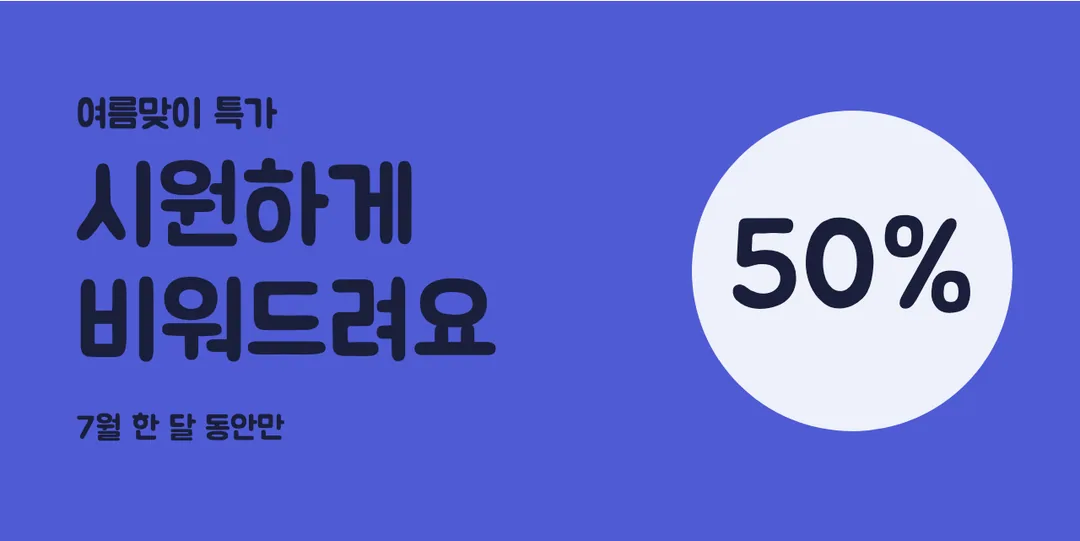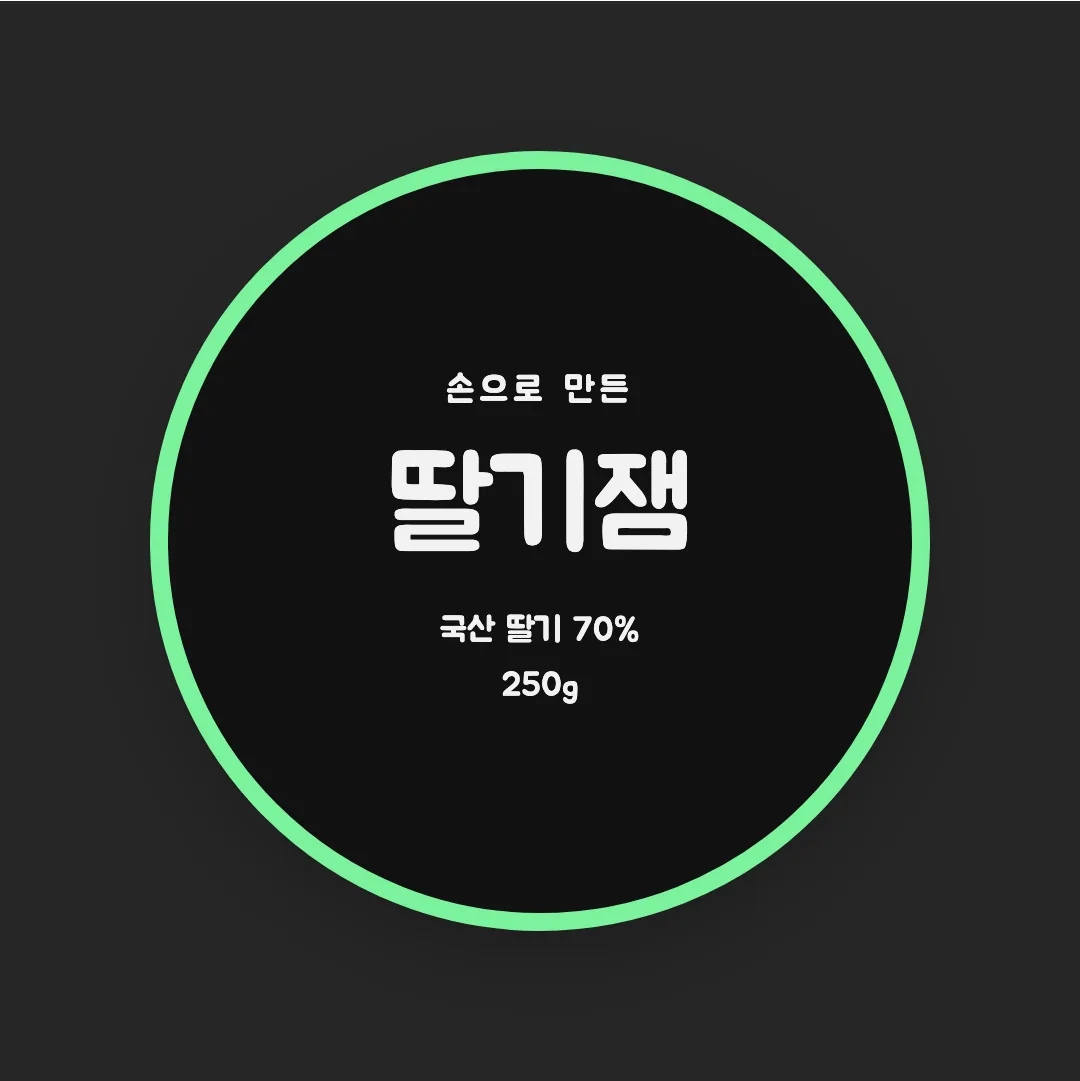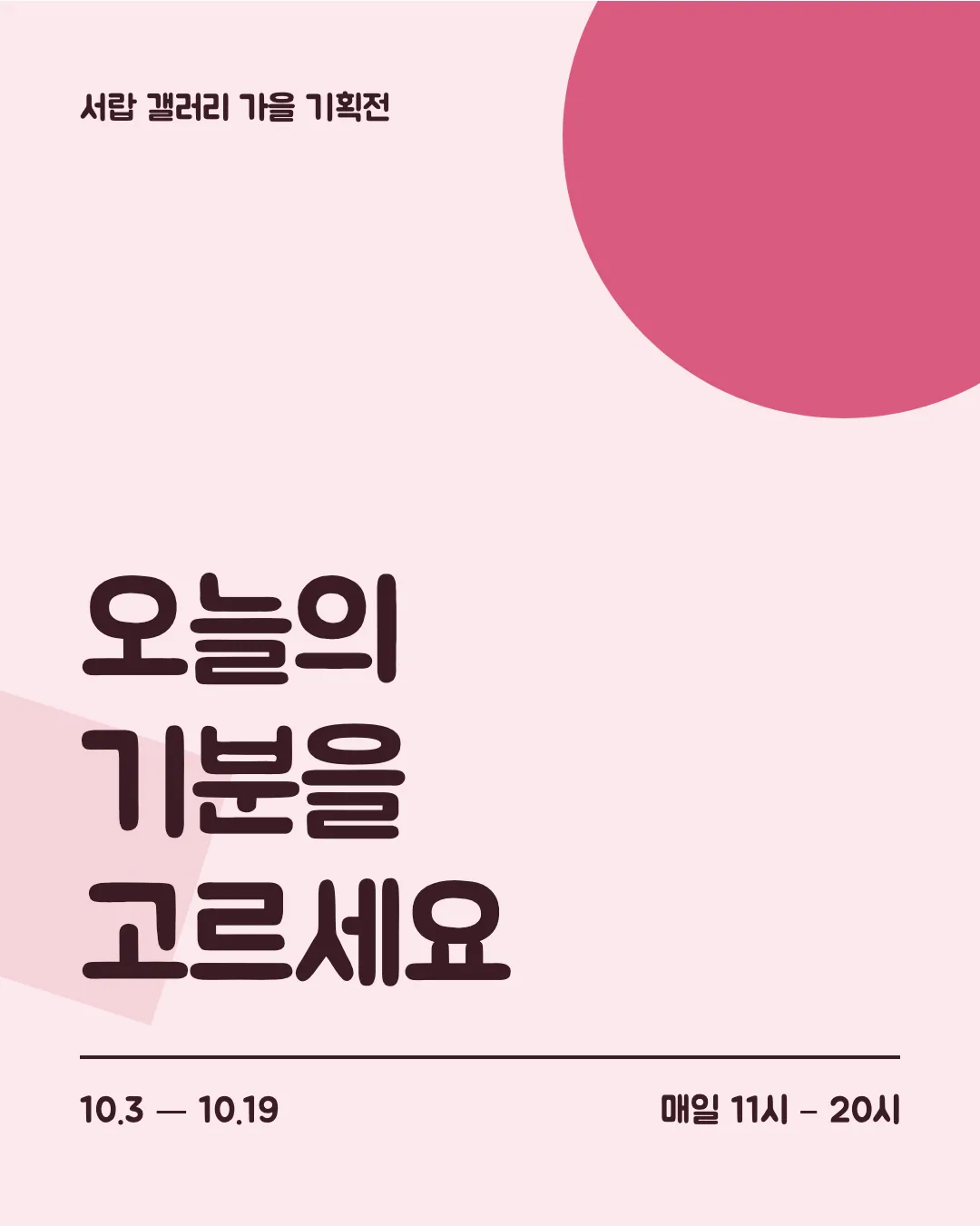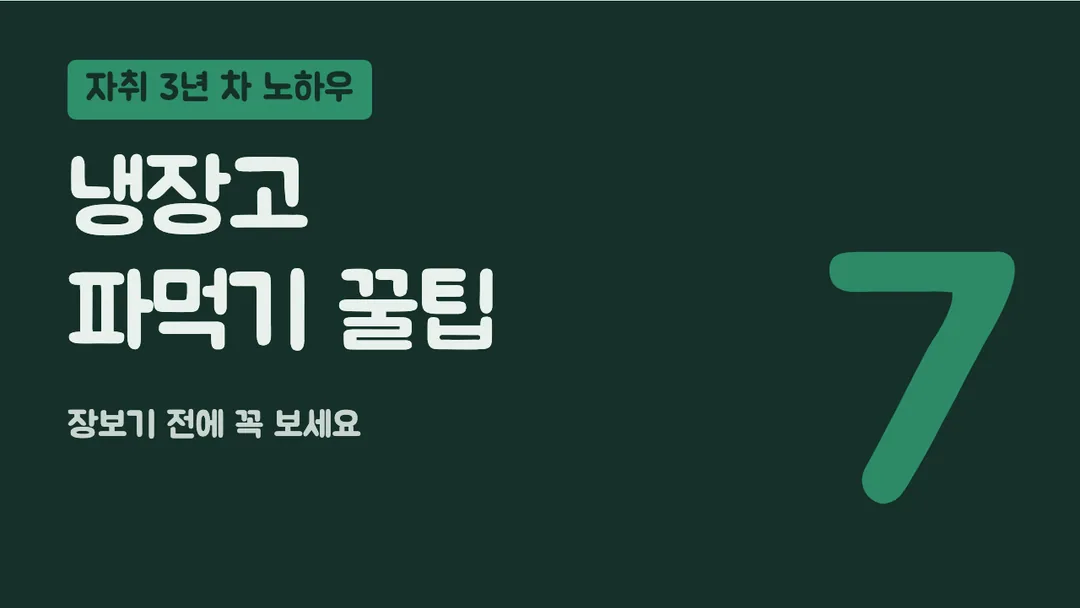
둥글둥글 도톰한 형태의 제목용 서체입니다. 친근하고 귀여운 인상이라 음식, 아동, 캐주얼 콘텐츠에 잘 맞습니다.
배달의민족 주아는 우아한형제들 (Woowahan Brothers)의 무료 장식체 폰트예요. 인쇄·웹사이트·포장지·영상·임베딩·BI/CI에 상업적으로 무료 사용할 수 있어요.
배달의민족 주아로 직접 만들어 본 디자인 예시예요. 이미지를 누르면 크게 볼 수 있어요.